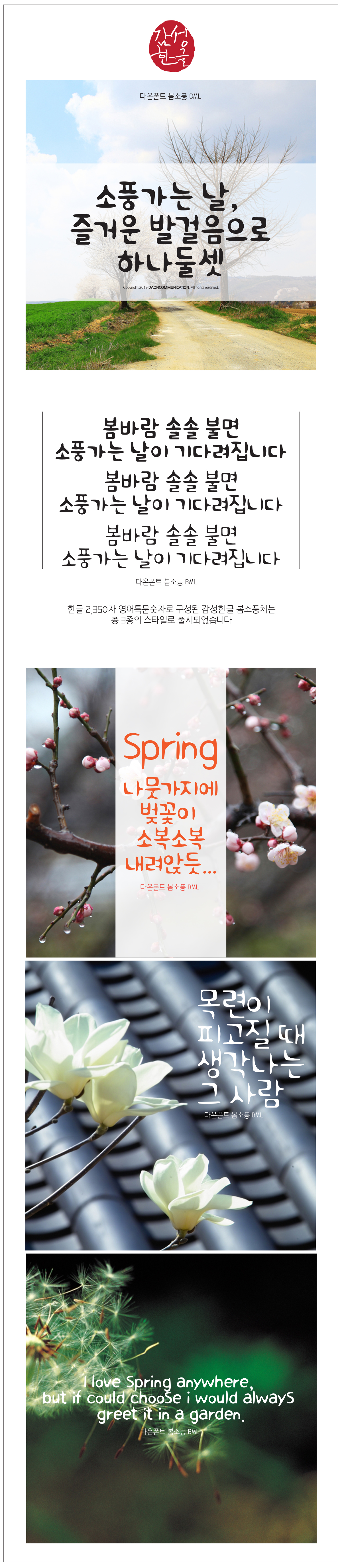
다온폰트 '봄소풍' 업데이트 안내
이번 업데이트 된 폰트는 다온폰트 '봄소풍'입니다.
다온폰트 '봄소풍'는 3가지 버전(B,M,L)으로 출시되었습니다.
한글 2,350자와 영문, 숫자, 특수문자 일부로 구성된 폰트로
어느덧 다가온 봄의 싱그러운 느낌을 살리고자 노력하였습니다.